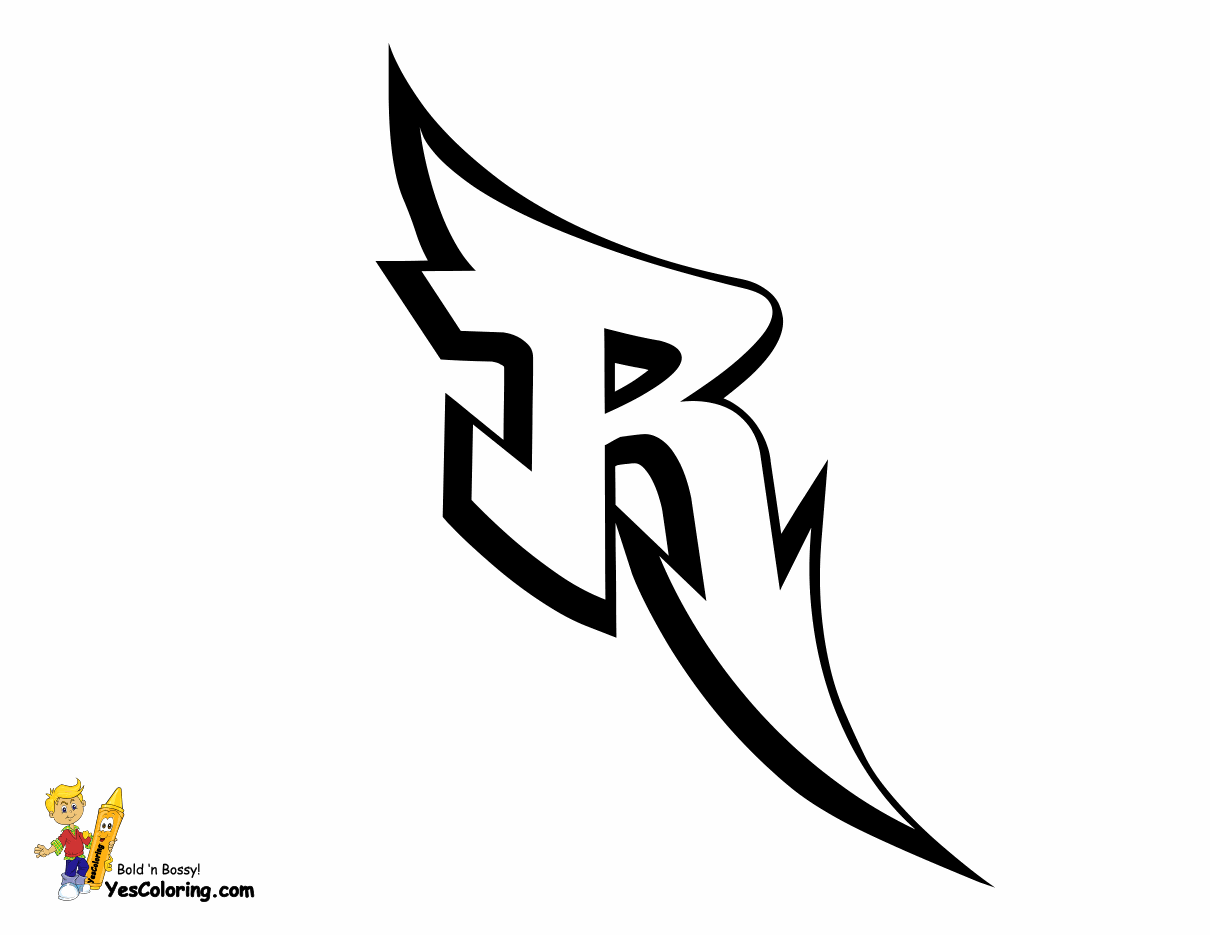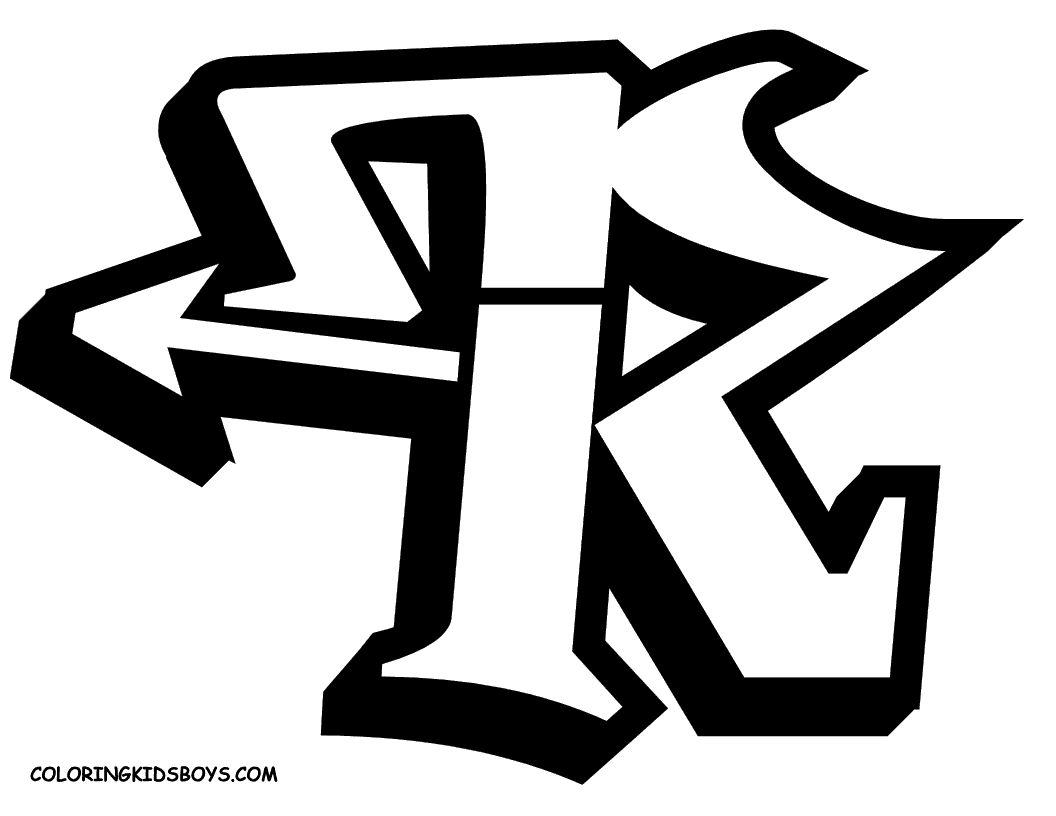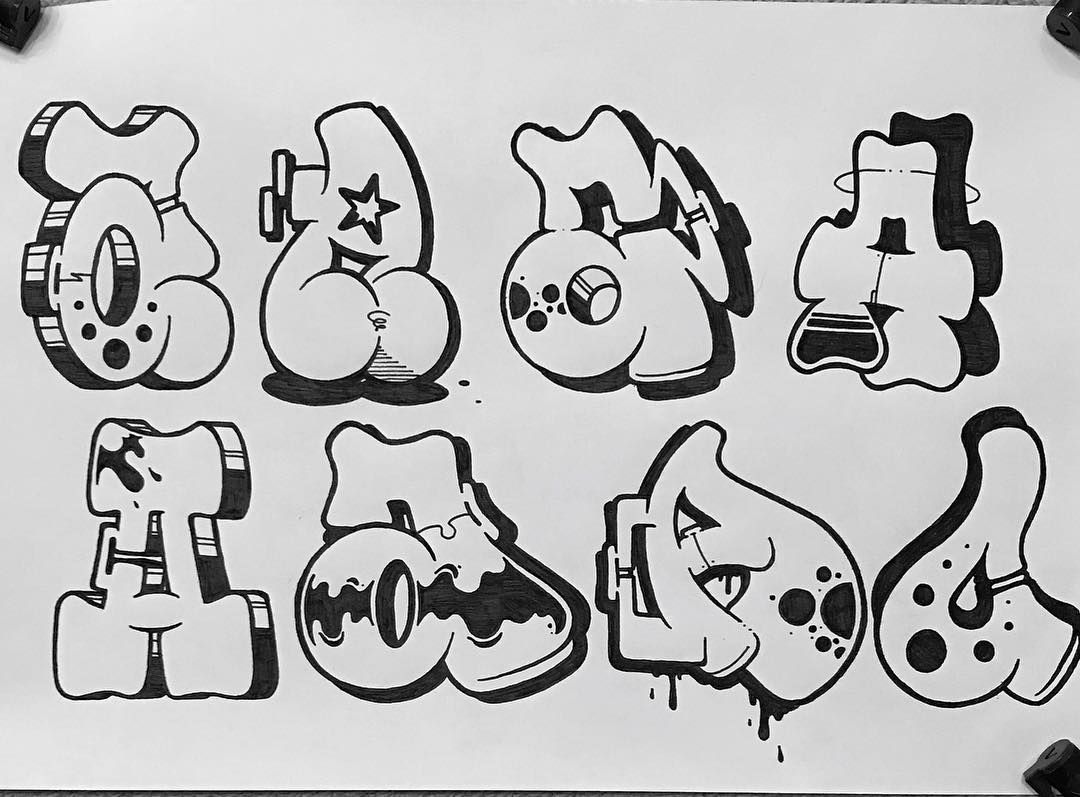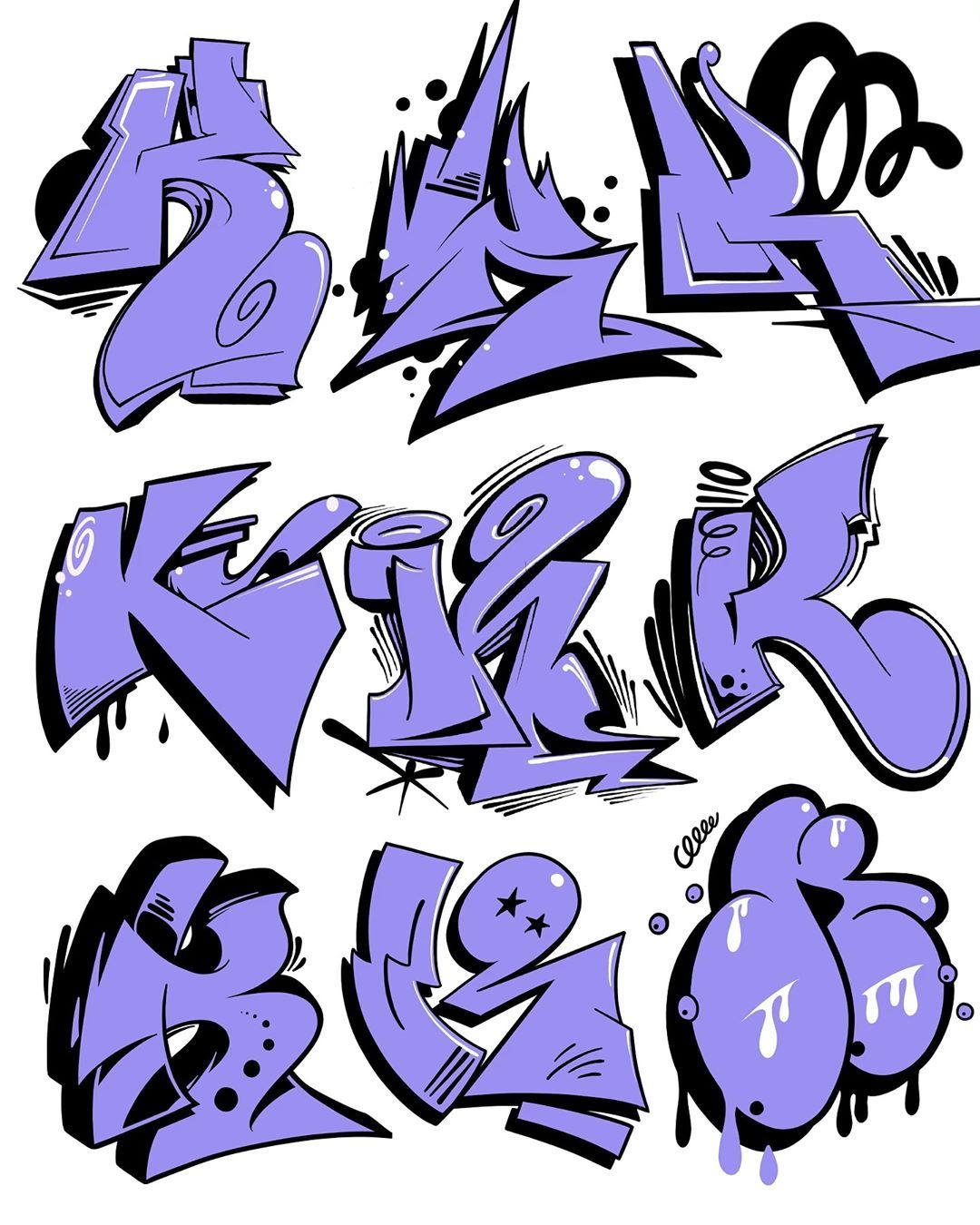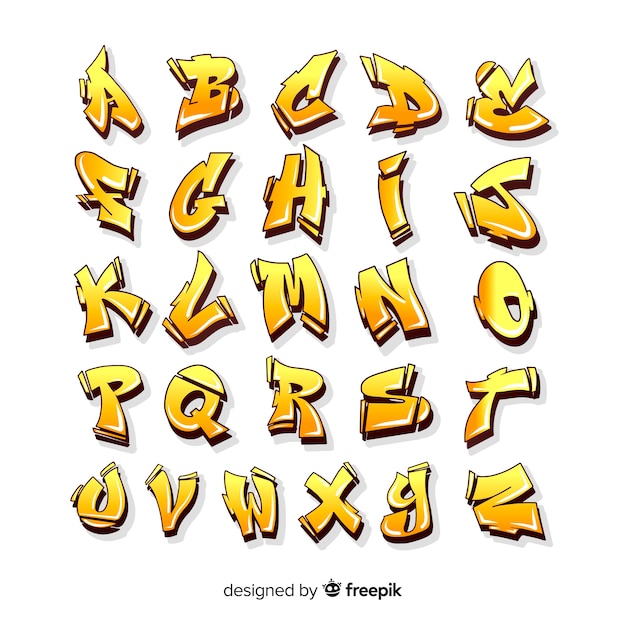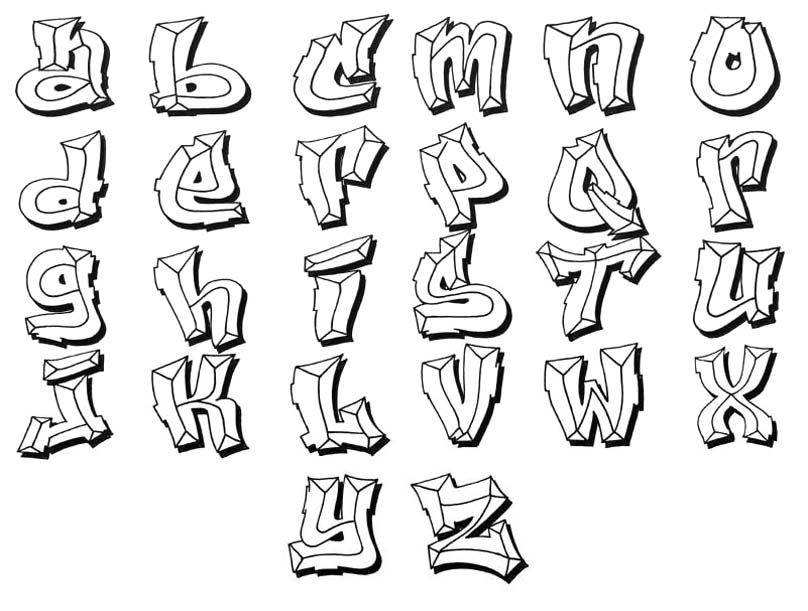
что думают в Благовещенске об уличном творчестве
Этот материал начался с высказывания губернатора Амурской области Василия Орлова на форуме «ProДФО».
Глава региона негативно отозвался о граффити, заявив, что их наличие на улицах города приведёт к вакханалии. Лучше, считает он, украшать стены муралами. Мы решили разобраться, так ли плохи маленькие надписи, и хуже ли они больших картин.
Бесконтрольные рисунки
На форуме «ProДФО» участники говорили об облике города, и речь зашла о граффити. Василий Орлов заявил, что он категорически против этого вида искусства.
Есть города, которые поддерживают граффити. Я категорически против. Муралы — да, они хороши. Граффити — нет, потому что их невозможно проконтролировать. Под эгидой граффити как искусства рисовать начинают все, кто рисовать не умеет в принципе. Скрывается за ними и реклама наркотиков со ссылками на те или иные запрещённые сайты. В итоге властям приходится тратить большие деньги, чтобы всё это убрать, — высказался губернатор.
Он отметил и другую разницу: уровень профессионализма художников, рисующих граффити и муралы.
Если большие картины на зданиях «абы кто не нарисует», и выглядят они красиво, то с надписями всё наоборот:
Допустим, предложим мы разрисовать людям некий «голый» забор. Все, кто захочет, это сделает. А когда забор закончится, пойдёт провокация: нарисовать где-то ещё. А если не закрасить свежие граффити на новой остановке, то скоро вокруг появятся ещё десятки таких надписей. В итоге все здания вокруг будут разукрашены, а это породит и мусор вокруг, и незаконные объявления на стенах. Все наши усилия по комфортной городской среде уничтожаются таким вандализмом.
Глава региона даже поделился результатом эксперимента, проведённого в одном из городов: на парковке у торгового центра под дворники машин клали рекламные листовки. В одном случае это делали, когда рядом находящаяся стена была исписана граффити, в другом — около чистого сооружения. В итоге в первом варианте люди бросали эти бумажки на землю, во втором — выкидывали в урну.
Мнение Cooltourspain о граффити-буквах
Мы считаем, что для того, чтобы добиться успеха в любом аспекте вашей жизни, вам нужно проявить настойчивость. Вот почему изучение того, как делать граффити-буквы, займет у вас много времени.
Мероприятие позволит собрать опытных художников, которые смогут провести мастер-классы для амурских авторов, поделиться опытом, а заодно и создадут картины, которые украсят город, — сказал губернатор.